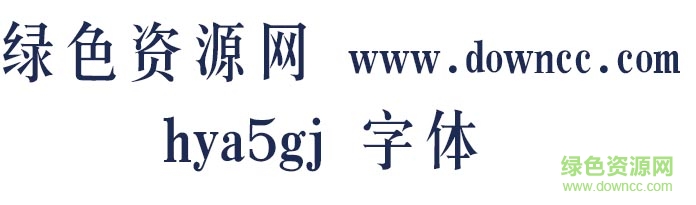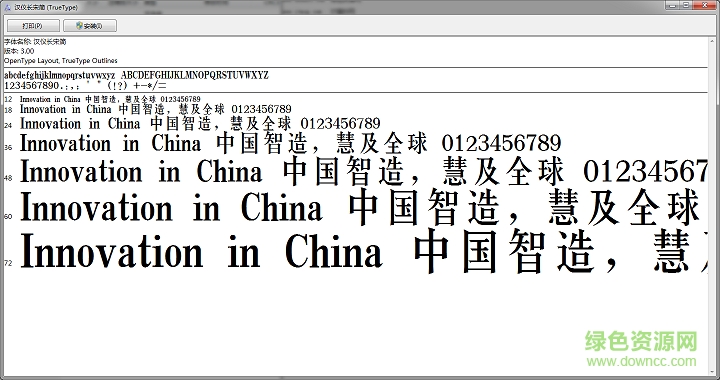
hya5gj字體是一款漢儀字體的英文名稱,中文為漢儀長(zhǎng)宋簡(jiǎn),字體寫出來的字是有點(diǎn)長(zhǎng)有點(diǎn)黑,也可以說是這款字體的獨(dú)特之處,有需要的朋友可以來綠色資源網(wǎng)下載。
hya5gj字體是一款獨(dú)特的電腦字體,字體線條柔和,筆畫靈活,寫出來的效果很不錯(cuò),優(yōu)雅而又不失個(gè)性。